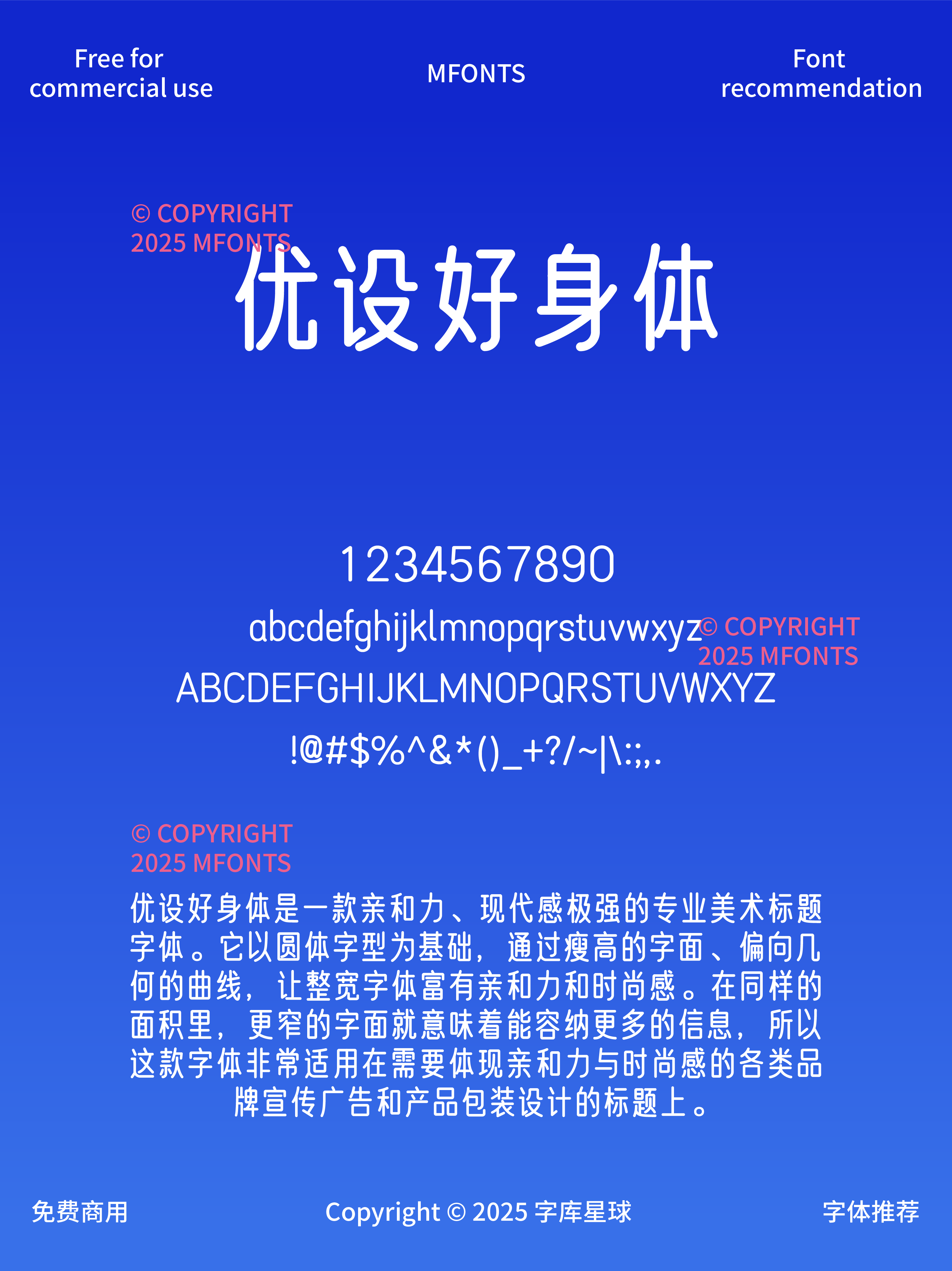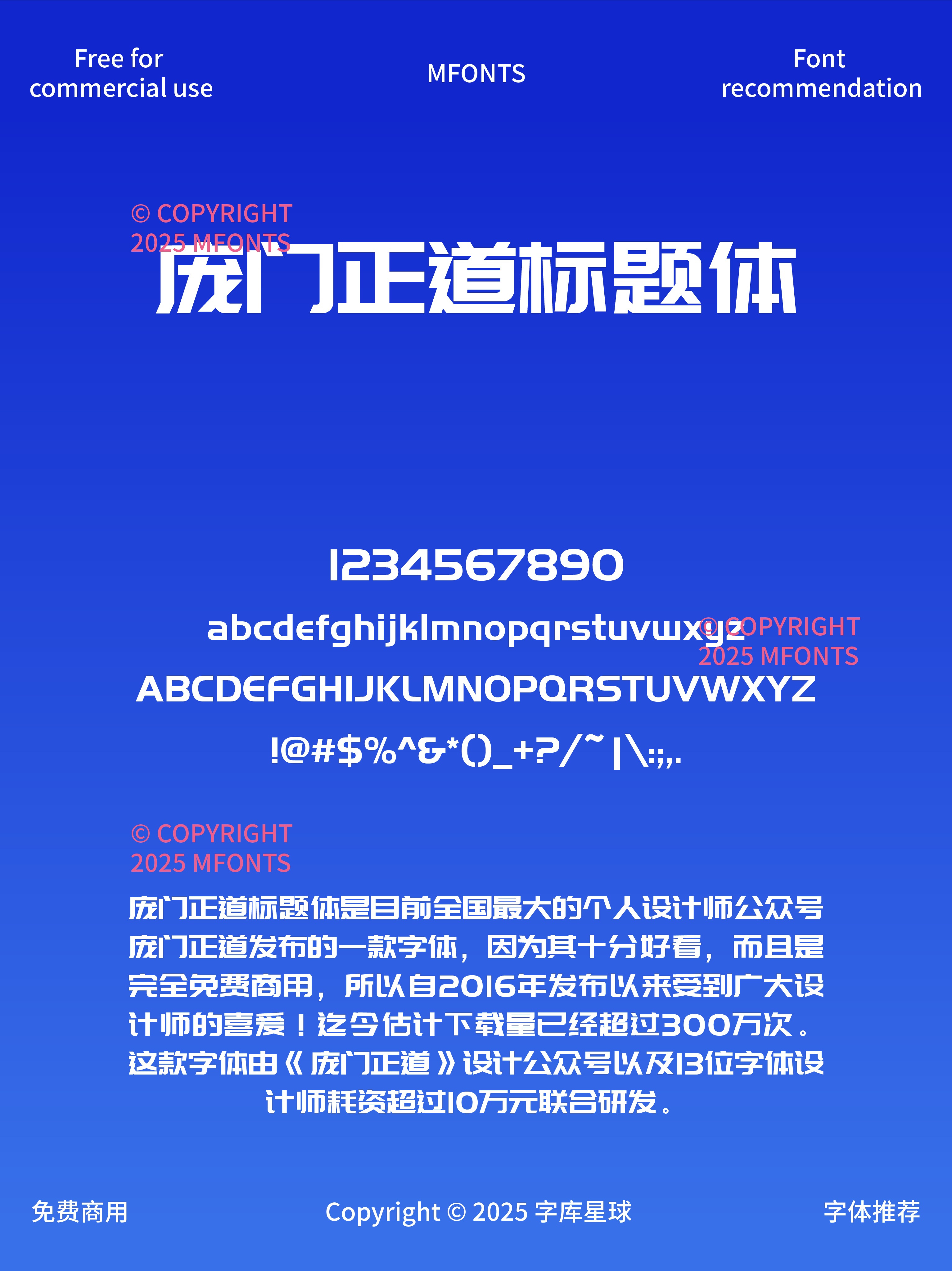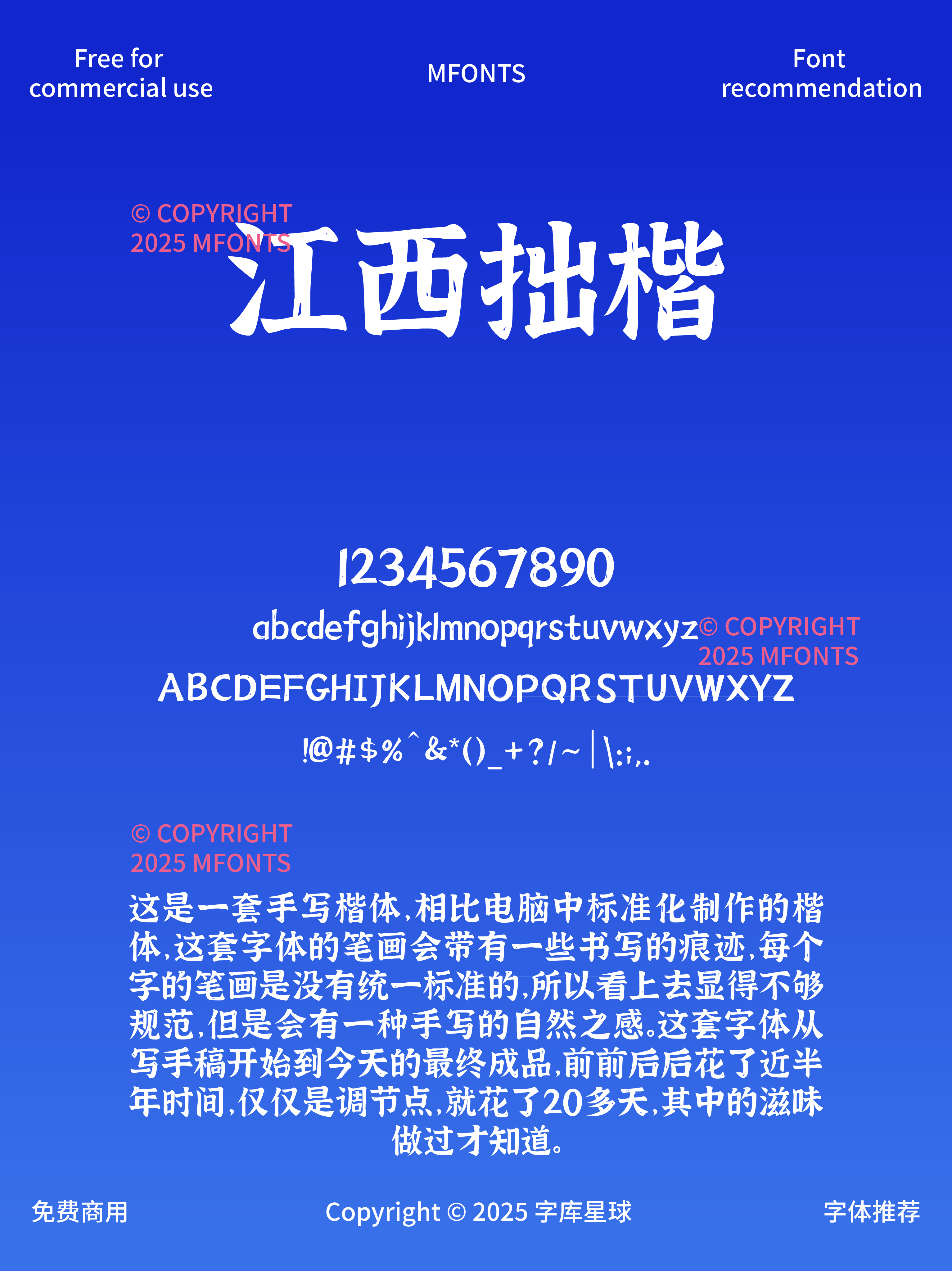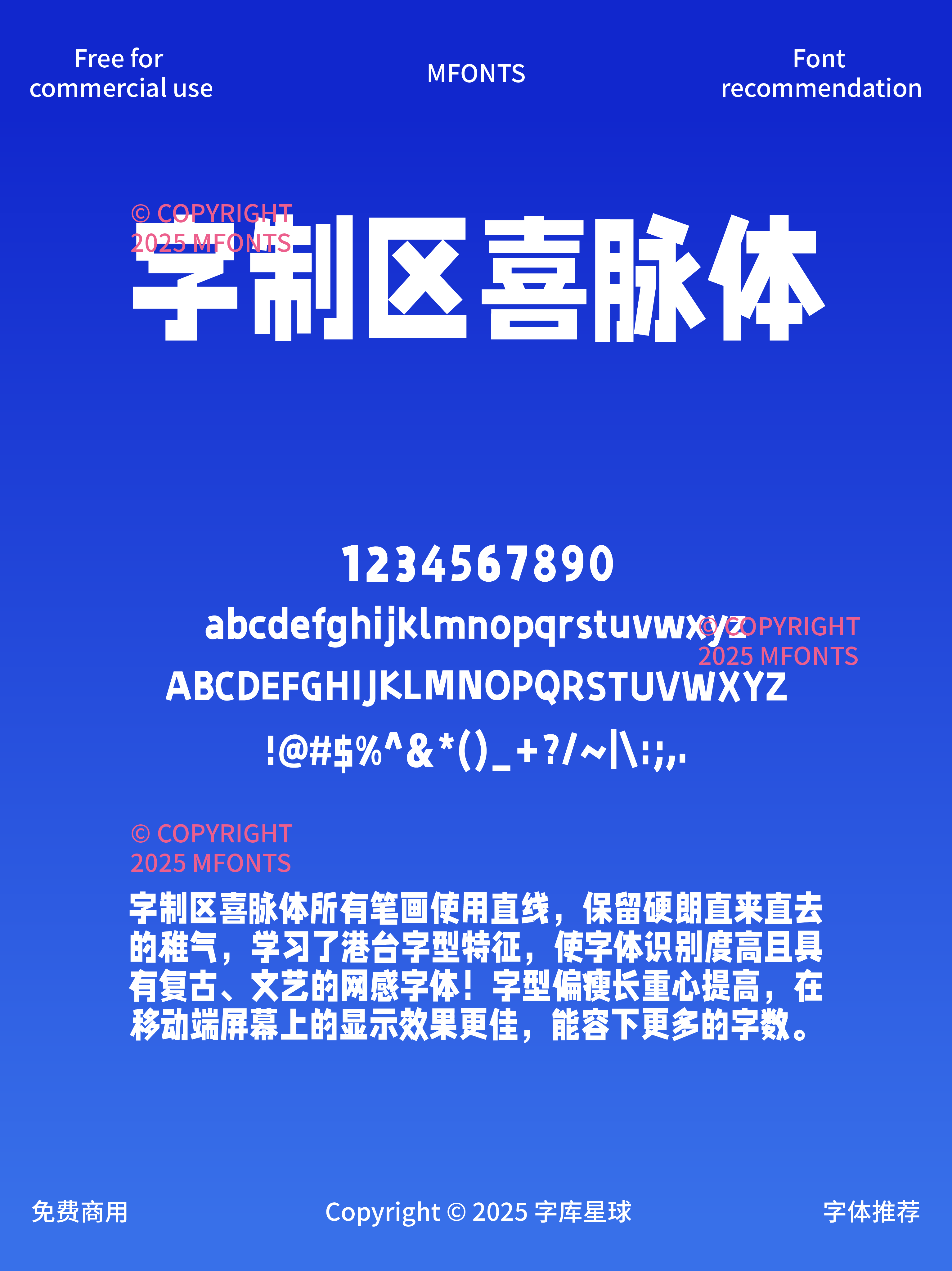
八款免费可商用618字体来袭火爆标题字体
宝子们,618 狂欢季即将开启,你的设计素材准备好了吗?今天给大家带来八款免费可商用的超赞字体,让你的 618 宣传标题瞬间脱颖而出。
字体笔画粗壮有力,充满力量感,特别适合用于突出促销力度的标题,比如 “618 疯狂折扣,直降 [X]%”,能一下子抓住消费者的眼球,激发他们的购买欲望。
独特的艺术风格,线条流畅且富有变化,为标题增添时尚感与创意,像 “618 时尚新风尚,潮流好物等你来” 这种标题,用它来展现再合适不过啦。